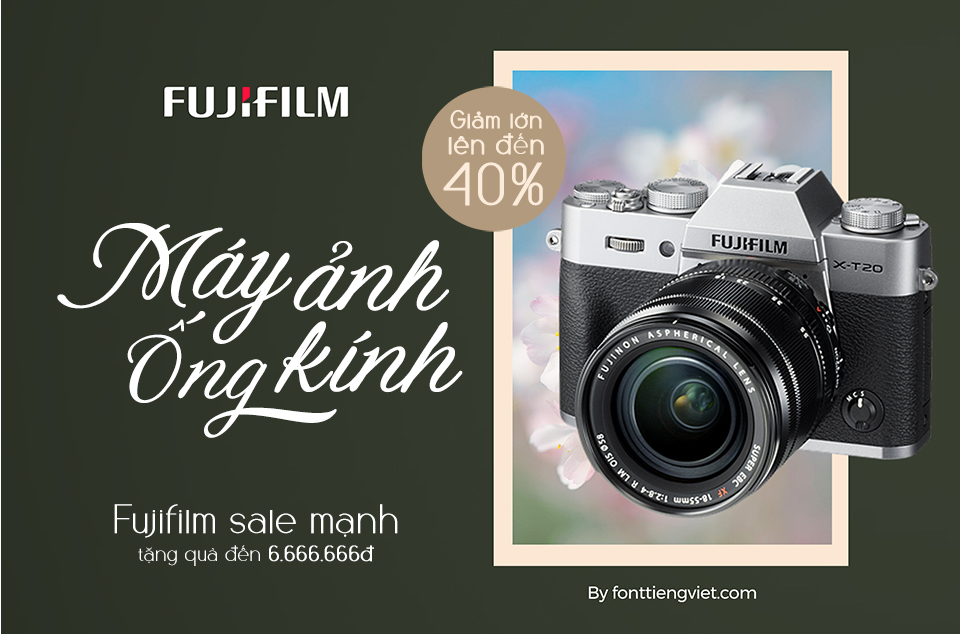
Combo font thiết kế chủ đề công nghệ 1
Tổng hợp Combo font thiết kế chủ đề công nghệ 1 miễn phí và chuyên nghiệp
Giới thiệu về Combo font thiết kế chủ đề công nghệ 1
Trong kỷ nguyên số hóa hiện nay, việc lựa chọn Font Miễn Phí phù hợp đóng vai trò then chốt trong việc truyền tải thông điệp của một sản phẩm công nghệ. Combo font thiết kế chủ đề công nghệ 1 được chúng tôi tuyển chọn kỹ lưỡng nhằm mang lại diện mạo hiện đại, tinh tế và đầy tính tương lai cho các dự án sáng tạo. Dù bạn đang thiết kế giao diện ứng dụng, làm banner quảng cáo linh kiện điện tử hay xây dựng bộ nhận diện thương hiệu cho startup phần mềm, bộ sưu tập này sẽ là công cụ đắc lực giúp nâng tầm thẩm mỹ. Những phông chữ này không chỉ đảm bảo tính thẩm mỹ cao mà còn được tối ưu hóa khả năng hiển thị trên nhiều loại màn hình khác nhau từ máy tính để bàn đến điện thoại di động.
Tại sao nên sử dụng Combo font thiết kế chủ đề công nghệ 1 trong sáng tạo
Đặc điểm của các font chữ mang hơi hướng kỹ thuật số
Đặc trưng lớn nhất của Combo font thiết kế chủ đề công nghệ 1 chính là những đường nét dứt khoát, hình khối rõ ràng và khoảng cách giữa các chữ cái được tính toán khoa học. Các font chữ này thường thuộc nhóm Sans-serif (không chân) với các góc bo tròn nhẹ hoặc cắt vát sắc sảo, tạo cảm giác về sự chính xác và tốc độ. Khi sử dụng bộ font này, người xem sẽ ngay lập tức liên tưởng đến các bảng mạch điện tử, trí tuệ nhân tạo và không gian vũ trụ rộng lớn. Điều này giúp tăng cường trải nghiệm người dùng và tạo niềm tin về sự chuyên nghiệp của doanh nghiệp trong mắt khách hàng.
Tính ứng dụng thực tế trong giáo dục và thiết kế
Đối với các bạn học sinh và sinh viên ngành thiết kế đồ họa, việc làm quen với Combo font thiết kế chủ đề công nghệ 1 là bước khởi đầu quan trọng. Bộ font này giúp các bạn dễ dàng tạo ra những bài thuyết trình ấn tượng hoặc các ấn phẩm truyền thông cho câu lạc bộ tin học. Sự đồng nhất về phong cách trong bộ combo giúp bố cục thiết kế trở nên hài hòa hơn, tránh tình trạng lạm dụng quá nhiều kiểu chữ gây rối mắt. Hơn nữa, việc sử dụng các font đã được việt hóa giúp việc soạn thảo nội dung tiếng Việt trở nên thuận tiện, không lo lỗi font hay sai định dạng dấu câu.
Cách phối hợp các phông chữ trong bộ sưu tập hiệu quả
Nguyên tắc tương phản và bổ trợ
Để tận dụng tối đa Combo font thiết kế chủ đề công nghệ 1, bạn nên kết hợp giữa một font chữ đậm, đậm nét cho tiêu đề và một font chữ mảnh, dễ đọc cho phần nội dung chi tiết. Sự tương phản này không chỉ giúp phân cấp thông tin rõ ràng mà còn tạo điểm nhấn thị giác mạnh mẽ. Ví dụ, một tiêu đề mang phong cách futuristic kết hợp cùng phần thân bài tối giản sẽ tạo nên một tổng thể rất “high-tech”. Hãy chú ý đến khoảng cách dòng (leading) và khoảng cách chữ (kerning) để đảm bảo văn bản luôn thoáng đãng và dễ tiếp cận nhất có thể đối với người đọc ở mọi lứa tuổi.
Kết luận về bộ font công nghệ chuyên nghiệp